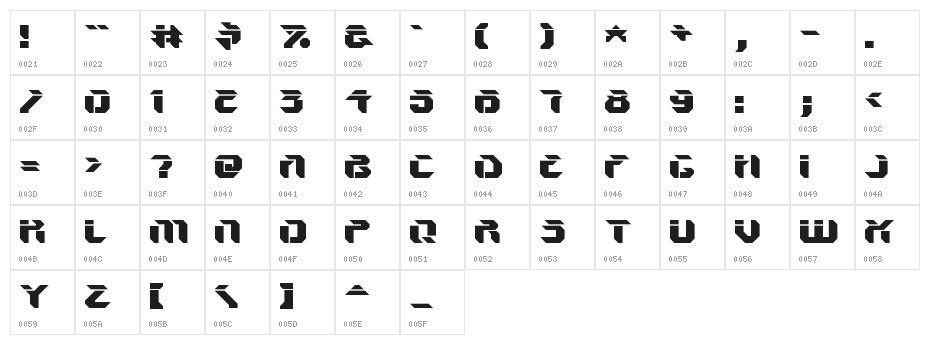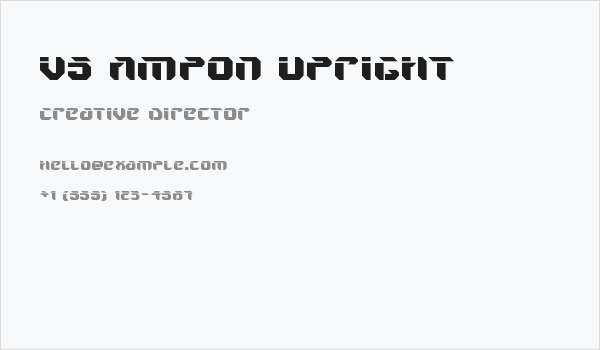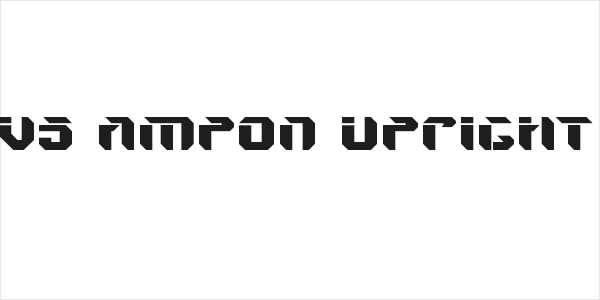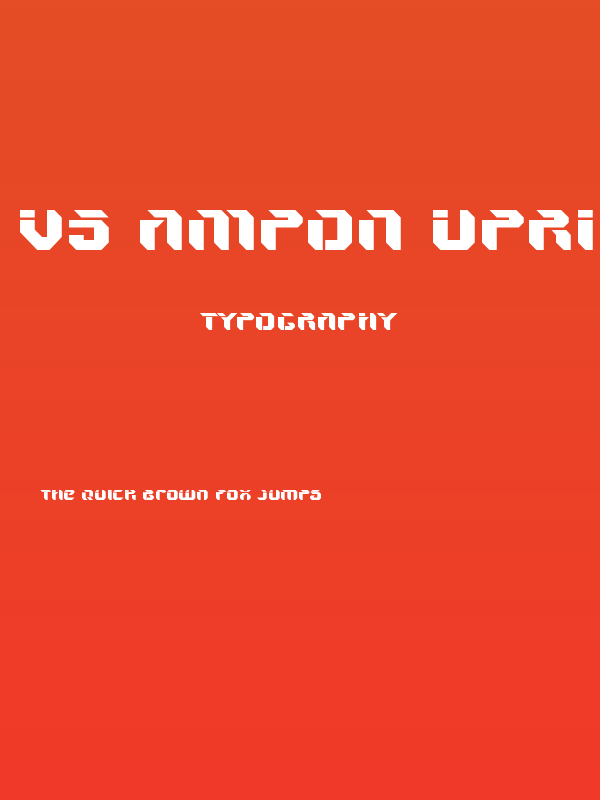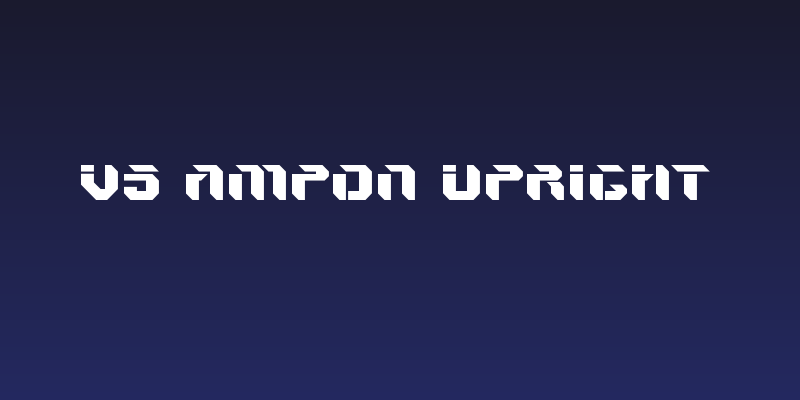
V5 Ampon Upright Font
| Stile generale | Futuristic |
| Progetti proposti | Ideal for branding, posters, video game graphics, and sci-fi themed designs. |